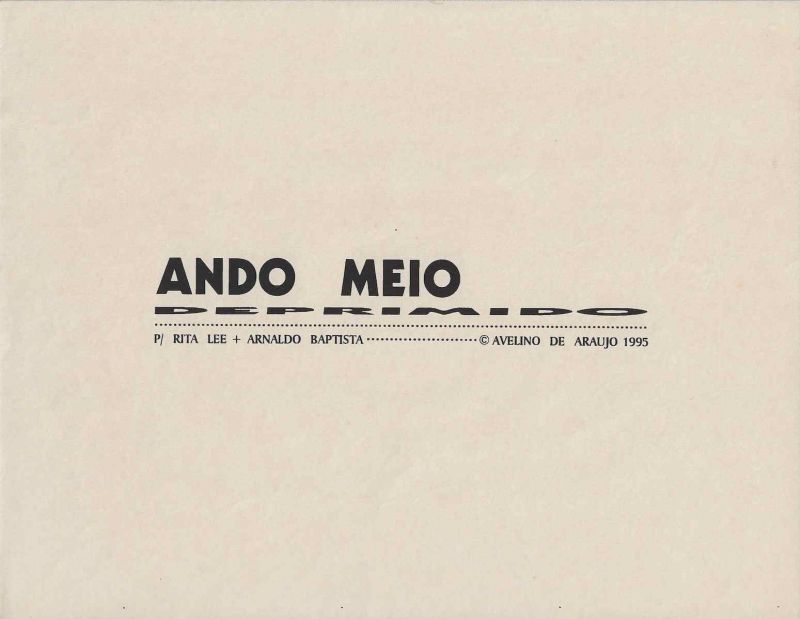
Ando Meio Deprimido é uma impressão gráfica de Avelino de Araújo realizada em 1995, vinculada à poesia visual, à poesia experimental, à arte conceitual, à tipografia e às investigações intersígnicas relacionadas ao campo do Poema Processo.
Ando Meio Deprimido é uma impressão gráfica de Avelino de Araújo realizada em 1995, vinculada à poesia visual, à poesia experimental, à arte conceitual, à tipografia e às investigações intersígnicas relacionadas ao campo do Poema Processo. A composição apresenta a expressão ANDO MEIO em letras maiúsculas negras de grande dimensão. A palavra DEPRIMIDO aparece logo abaixo, submetida a forte compressão vertical, como se tivesse sido achatada, rebaixada ou pressionada contra a linha de base. A transformação tipográfica representa visualmente o significado emocional da palavra. Deprimido deixa de ser apenas uma informação verbal e passa a demonstrar graficamente uma condição de queda, redução, peso, abatimento e perda de energia. Avelino de Araújo estabelece uma relação direta entre conteúdo e forma, fazendo com que a palavra execute aquilo que anuncia. A expressão Ando meio deprimido possui caráter cotidiano e coloquial, podendo descrever estado de tristeza, desânimo, cansaço, isolamento ou instabilidade emocional. A presença da palavra meio introduz ambiguidade, pois pode indicar intensidade parcial e também posição intermediária. Na composição, o termo aparece entre Ando e Deprimido, reforçando sua função de passagem entre movimento e imobilidade. O verbo andar sugere deslocamento e continuidade, enquanto a palavra deformada abaixo transmite peso e paralisação. Essa oposição cria tensão entre seguir em frente e permanecer abatido. A linha pontilhada situada sob a palavra comprimida funciona como limite, pausa, horizonte ou superfície sobre a qual o termo parece ter sido pressionado. Na parte inferior aparece a dedicatória para Rita Lee e Arnaldo Baptista, artistas ligados à história do rock brasileiro, da música experimental e do grupo Os Mutantes. Essa referência aproxima a obra da cultura musical brasileira e pode estabelecer um diálogo afetivo, irônico ou poético com temas de comportamento, liberdade, criação e estado emocional. A composição utiliza poucos elementos, forte contraste entre preto e fundo claro e ampla área vazia, concentrando a leitura no jogo tipográfico. Ando Meio Deprimido integra a produção de Avelino de Araújo baseada na transformação de palavras, letras, proporções e códigos gráficos em imagens poéticas. Palavras chave para indexação: Avelino de Araújo, Ando Meio Deprimido, 1995, impressão gráfica, poesia visual brasileira, poema visual, poesia experimental, arte conceitual, Poema Processo, palavra deprimido, depressão visual, tristeza, desânimo, estado emocional, tipografia experimental, deformação tipográfica, compressão vertical, palavra imagem, texto imagem, Rita Lee, Arnaldo Baptista, Os Mutantes, rock brasileiro, música experimental brasileira, semiótica, intersigno, comunicação visual, arte gráfica brasileira, múltiplo gráfico, arquivo de poesia visual, arte brasileira do século vinte.TEXT FOR THE SALSA PROGRAM IN ENGLISH: I Feel Somewhat Depressed is a graphic print by Avelino de Araújo produced in 1995 and associated with visual poetry, experimental poetry, conceptual art, typography and intersemiotic investigations connected with the field of the Poema Processo movement. The composition presents the Portuguese expression ANDO MEIO in large black capital letters. The word DEPRIMIDO, meaning depressed, appears immediately below and is subjected to intense vertical compression, as though it had been flattened, lowered or pressed against the baseline. The typographic transformation visually represents the emotional meaning of the word. Depressed no longer functions only as verbal information and instead graphically demonstrates a condition of descent, reduction, weight, discouragement and loss of energy. Avelino de Araújo establishes a direct relationship between content and form, causing the word to perform what it communicates. The expression Ando meio deprimido has an everyday and conversational character and may describe sadness, discouragement, exhaustion, isolation or emotional instability. The word meio introduces ambiguity because it may indicate partial intensity and also an intermediate position. In the composition, the term appears between Ando and Deprimido, reinforcing its role as a passage between movement and immobility. The verb andar suggests movement and continuity, while the distorted word below communicates weight and paralysis. This opposition creates tension between continuing forward and remaining emotionally lowered. The dotted line beneath the compressed word functions as a boundary, pause, horizon or surface against which the word seems to have been pressed. The lower section contains a dedication to Rita Lee and Arnaldo Baptista, artists connected with the history of Brazilian rock, experimental music and the group Os Mutantes. This reference connects the work with Brazilian musical culture and may establish an emotional, ironic or poetic dialogue with themes of behavior, freedom, creation and emotional states. The composition uses few elements, strong contrast between black and the light background and extensive empty space, focusing attention on the typographic wordplay. I Feel Somewhat Depressed belongs to Avelino de Araújo
Impressão gráfica em tinta preta sobre papel claro de tonalidade levemente amarelada. A composição ocupa uma faixa horizontal na região central da folha. Na parte superior aparecem as palavras ANDO e MEIO em letras maiúsculas, espessas e amplamente espaçadas. A palavra DEPRIMIDO encontra se abaixo, com os caracteres intensamente achatados no sentido vertical e estendidos horizontalmente. A deformação dificulta parcialmente a leitura e cria a aparência de uma palavra comprimida pelo próprio peso. Uma sequência de pontos aparece sob a área tipográfica e prolonga visualmente a composição. Na linha inferior encontra se a dedicatória P RITA LEE ARNALDO BAPTISTA, seguida por nova sequência pontilhada, pelo símbolo de autoria, pelo nome AVELINO DE ARAUJO e pelo ano 1995. A maior parte do suporte permanece sem impressão, reforçando o isolamento da frase e a economia visual da obra. O papel apresenta discretas ondulações, vincos, pequenas manchas, alterações de tonalidade e sinais leves de envelhecimento e manuseio. A peça pode ser classificada como poema visual, impressão de artista, múltiplo gráfico, estudo tipográfico, homenagem musical e documento conceitual, sendo relevante para pesquisas sobre Avelino de Araújo, Poema Processo, poesia visual, Rita Lee, Arnaldo Baptista, Os Mutantes, música brasileira, tipografia, linguagem, semiótica e produção gráfica brasileira.OBSERVATION TEXT IN ENGLISH: Graphic print in black ink on light colored paper with a slightly yellowed tone. The composition occupies a horizontal band in the central region of the sheet. The words ANDO and MEIO appear in the upper section in thick, widely spaced capital letters. The word DEPRIMIDO appears below with its characters intensely flattened vertically and extended horizontally. The deformation partially reduces legibility and creates the appearance of a word compressed by its own weight. A sequence of dots appears beneath the typographic area and visually extends the composition. The lower line contains the dedication P RITA LEE ARNALDO BAPTISTA, followed by another dotted sequence, the authorship symbol, the name AVELINO DE ARAUJO and the year 1995. Most of the support remains unprinted, reinforcing the isolation of the phrase and the visual economy of the work. The paper presents slight undulations, creases, small stains, changes in tone and subtle signs of aging and handling. The piece may be classified as a visual poem, artist print, graphic multiple, typographic study, musical tribute and conceptual document, making it relevant to research on Avelino de Araújo, Poema Processo, visual poetry, Rita Lee, Arnaldo Baptista, Os Mutantes, Brazilian music, typography, language, semiotics and Brazilian graphic production.
I Feel Somewhat Depressed is a graphic print by Avelino de Araújo produced in 1995 and associated with visual poetry, experimental poetry, conceptual art, typography and intersemiotic investigations connected with the field of the Poema Processo move